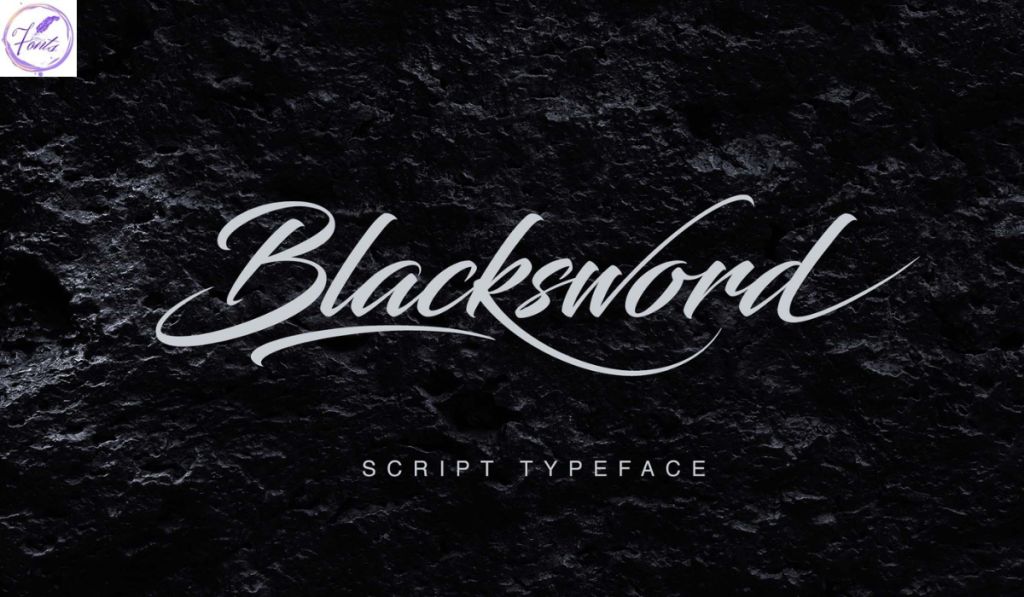
Tác giả: Youssef Habchi
Ngày phát hành: 2022
Bộ Font: 1FTV VIP
Phân loại: Độc đáo, mạnh mẽ
Kiểu chữ: Viết tay, calligraphy
Độ dày: Blacksword
Font 1FTV VIP Blacksword thuộc bộ font Blacksword là một kiểu ký tự thuộc loại Latin và được phân loại là calligraphy. Font này được thiết kế bởi Mikrojihad và phát hành vào ngày 26/07/2022. Blacksword là font chữ Việt hóa được hỗ trợ ngôn ngữ tiếng Việt và có tổng cộng 284 ký tự. Font này có kích thước linh hoạt, có thể điều chỉnh theo nhu cầu sử dụng. Mặc dù miễn phí cho sử dụng cá nhân, nhưng nếu muốn sử dụng cho mục đích thương mại, bạn cần phải mua bản quyền. Bài viết này của fonts.com.vn gửi bạn link tải Font 1FTV VIP Blacksword miễn phí.